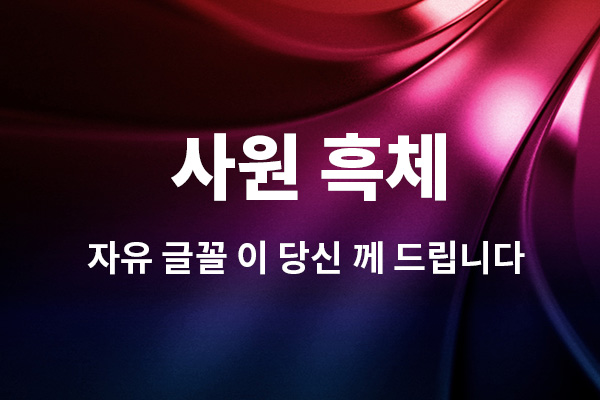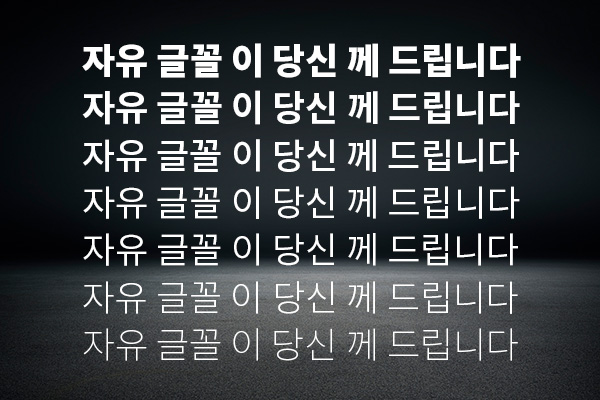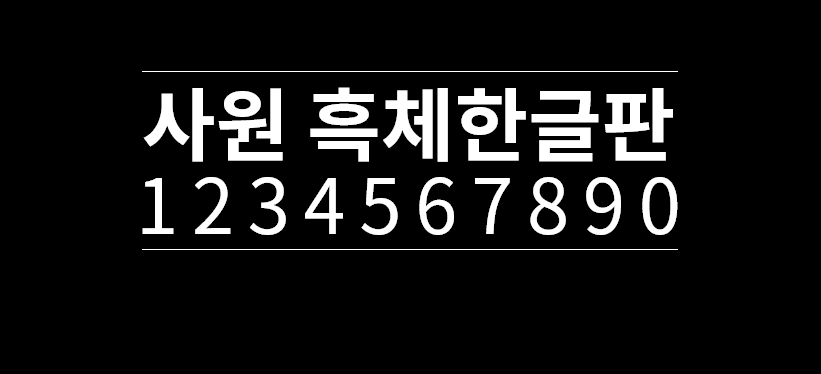
思源黑体-韩文版字体介绍
思源黑体-韩文版是由adobe与谷歌领导开发的开源字体,从2014年至今经过不断的修正与完善,影响越来越大,像思源柔黑、思源真黑等字体就是此开源的基础上衍化而来的,实用性非常高。 有七种字体粗细(ExtraLight、Light、Normal、Regular、Medium、Bold 和 Heavy),完全支持日文、韩文、繁体中文和简体中文,还包括来自 Source Sans字体家族的拉丁文、希腊文和西里尔文字形共65536个字形。Google将其命名为Noto SansCJK,作为Google的Noto字体家族的成员。Adobe则命名为Source Han Sans,作为Adobe的Source字体家族的一员。Adobe拥有字体设计的版权。发布的字体文件则可以不受限制的免费使用。 安装后软件中找不到的话,可以找“본고딕 KR”或“Source Han Sans KR”。
思源黑体-韩文版字体应用示例